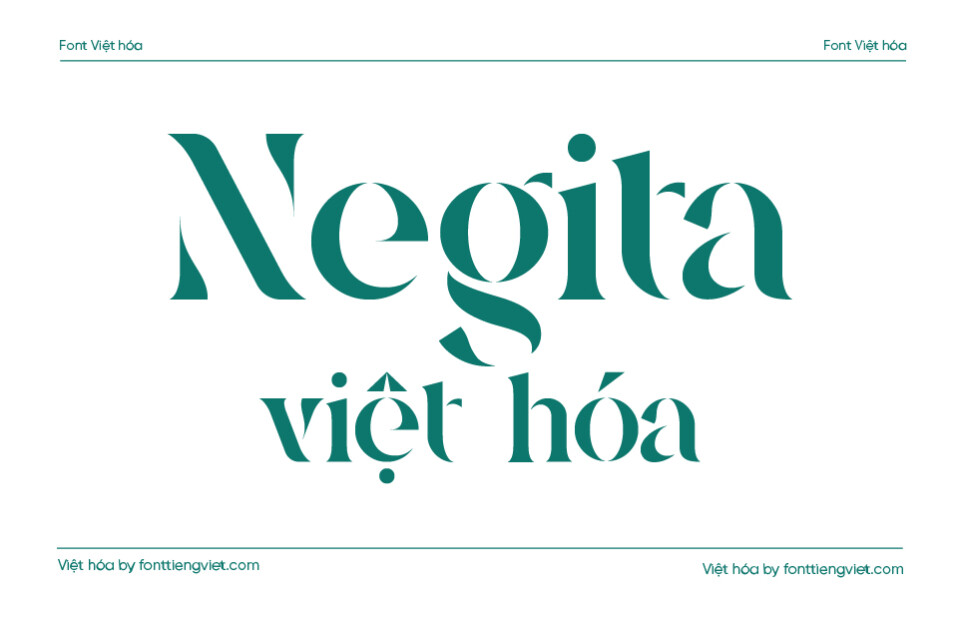
Font Việt hóa 1FTV VIP Negita – Bộ font sang trọng cho thiết kế đồ họa chuyên nghiệpTrong thế giới thiết kế đồ họa hiện đại, việc tìm kiếm một bộ chữ vừa mang tính thẩm mỹ cao vừa hỗ trợ đầy đủ tiếng Việt là điều vô cùng quan trọng đối với các nhà sáng tạo. Font Việt hóa 1FTV VIP Negita nổi lên như một lựa chọn hàng đầu nhờ sự kết hợp hoàn mỹ giữa phong cách cổ điển và hơi thở đương đại. Nếu bạn đang tìm kiếm một Font Miễn Phí để nâng tầm dự án cá nhân hoặc thương mại, thì đây chính là bộ gõ không thể bỏ qua. Sự tinh tế trong từng đường nét của Negita giúp mọi văn bản trở nên cuốn hút và dễ đọc hơn bao giờ hết trên mọi nền tảng hiển thị.Khám phá vẻ đẹp đặc trưng của Font Việt hóa 1FTV VIP NegitaBộ Font Việt hóa 1FTV VIP Negita thuộc dòng Serif cách tân với các đường nét thanh mảnh đan xen cùng những điểm nhấn đậm chắc chắn. Đặc điểm nhận dạng lớn nhất của bộ font này chính là sự cân bằng tuyệt đối giữa các khoảng trống, tạo nên cảm giác thoáng đãng nhưng vẫn rất uy nghiêm. Đội ngũ 1FTV đã kỳ công thực hiện việc Việt hóa, đảm bảo các dấu câu tiếng Việt được đặt đúng vị trí, không bị lệch hay lỗi hiển thị khi gõ các ký tự phức tạp.Tính ứng dụng đa dạng trong thiết kếNhờ vẻ ngoài lịch lãm, Font Việt hóa 1FTV VIP Negita cực kỳ phù hợp cho các tiêu đề bìa tạp chí, thiết kế logo thương hiệu thời trang cao cấp hoặc các thiệp mời sự kiện quan trọng. Bên cạnh đó, các bạn học sinh và sinh viên cũng có thể sử dụng bộ font này để trang trí slide thuyết trình, giúp bài làm trở nên chuyên nghiệp và ấn tượng hơn trong mắt giáo viên. Khả năng hiển thị sắc nét của nó cũng là điểm cộng lớn khi ứng dụng vào các giao diện website đòi hỏi sự sang trọng và tinh tế.Lợi ích khi sử dụng Font Việt hóa 1FTV VIP NegitaViệc sử dụng Font Việt hóa 1FTV VIP Negita mang lại sự đồng bộ tối đa cho các sản phẩm truyền thông của bạn. Thay vì lo lắng về vấn đề lỗi font hệ thống khi gõ dấu, phiên bản VIP này đã tối ưu hóa mọi bảng mã phổ biến nhất hiện nay. Ngoài ra, cấu trúc chữ của Negita còn giúp tối ưu hóa thị giác, giảm mỏi mắt cho người đọc khi tiếp cận các đoạn văn bản dài. Đây là một yếu tố quan trọng giúp thông điệp của bạn được truyền tải trọn vẹn và hiệu quả nhất đến khách hàng mục tiêu.Lưu ý khi cài đặt và sử dụng hiệu quảĐể phát huy tối đa vẻ đẹp của Font Việt hóa 1FTV VIP Negita, bạn nên kết hợp nó với các font chữ không chân (Sans-serif) đơn giản cho phần nội dung chi tiết. Sự tương phản này sẽ làm nổi bật phần tiêu đề sử dụng Negita, tạo nên một bố cục phân cấp thị giác rõ ràng. Khi cài đặt, hãy đảm bảo bạn đã giải nén tệp tin và cài đặt đầy đủ các định dạng .otf hoặc .ttf để tương thích tốt nhất với các phần mềm thiết kế như Adobe Photoshop, Illustrator hay Canva.Kết luận về bộ Font Việt hóa 1FTV VIP NegitaTóm lại, đây là một tài nguyên quý giá dành cho bất kỳ ai đang hoạt động trong lĩnh vực sáng tạo nội dung và thiết kế. Với sự hỗ trợ tận tình từ cộng đồng font chữ tại Việt Nam, bạn có thể dễ dàng tải về và trải nghiệm những tính năng ưu việt của nó ngay hôm nay. Hy vọng rằng bộ chữ này sẽ trở thành nguồn cảm hứng mới cho những tác phẩm nghệ thuật sắp tới của bạn. Đừng quên truy cập vào Font Miễn Phí, Font Việt Hóa, Font Việt hóa 1FTV VIP Negita để sở hữu ngay bộ công cụ tuyệt vời này và bắt đầu hành trình sáng tạo không giới hạn của mình.
Font Việt hóa 1FTV VIP Negita